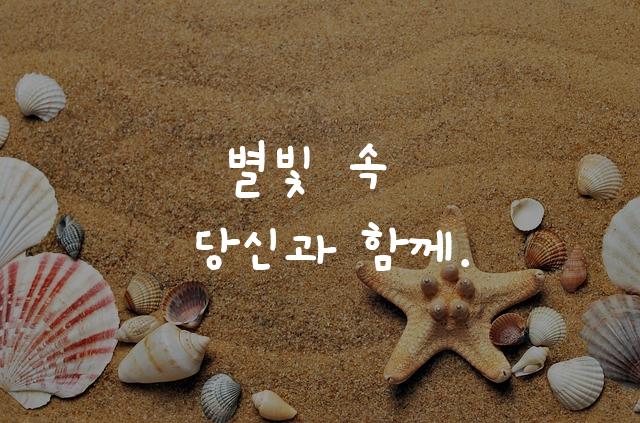
J해바라기는 직지소프트에서 제작한 폰트로, 부드러운 곡선과 섬세한 라인이 특징입니다. 디자인에서 감성적인 요소를 강조하고자 할 때 이상적입니다.
J해바라기은(는)
계열의 생김새를 가지고 있으며
어린이 책, 인사말 카드 등에서 자주 활용되며, 효과적인 메시지 전달에 적합합니다.
이 폰트는 라이프스타일, 유아/가족 분야에 잘 어울리며,
친근한, 귀여운 느낌을 담고 있는 것이 특징입니다.